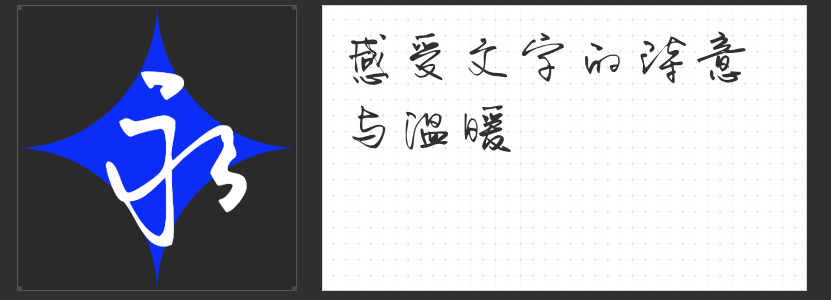
小豆岛手写字体推荐:四款风格迥异的设计利器
在商业设计中,手写字体的独特性和人文温度能瞬间提升作品的艺术质感。小豆岛系列字体以“传统笔意与现代设计融合”为核心理念,推出多款风格鲜明的手写字体,尤其适合海报、包装、品牌标识等场景。以下四款字体各具特色,可满足不同设计需求。
一、小豆岛默陌枝桠简
这款字体以“疏密有致”为设计核心,通过运笔节奏塑造线条粗细与节点,呈现出枯枝藤蔓般的自然形态。其水墨书写风格既有传统书法的写意感,又融入现代设计的留白美学,适合茶饮、文创、禅意主题的设计。例如,在茶包装中,小豆岛默陌枝桠简的飞白效果能传递“古朴自然”的品牌调性;在短视频字幕中,其灵动的笔触可增强画面叙事感。
二、小豆岛默陌乐童简
小豆岛默陌乐童简采用“上松下紧”的儿童字结构,笔画简单稚拙且宽细一致,完美复刻孩童书写时的天真感。这款字体尤其适合母婴产品、儿童绘本、教育机构等场景。例如,某早教品牌LOGO使用小豆岛默陌乐童简后,圆润的笔画与倾斜的字体结构传递出“活泼探索”的品牌理念;在电商促销海报中,其稚拙感能拉近与年轻家长的距离。
三、小豆岛默陌纸鸢草书简
小豆岛默陌纸鸢草书简以“连笔流畅”为特色,笔画恣意舒展如风筝线般飘逸,中宫放大与笔画加粗的设计则提升了辨识度。这款字体兼具艺术性与实用性,适合运动品牌、音乐节、快消品等动态场景。例如,某运动鞋广告使用小豆岛默陌纸鸢草书简后,飞白的笔触与倾斜的字体结构强化了“速度与力量”的视觉冲击;在社交媒体短视频中,其流畅的连笔可提升字幕的阅读流畅度。
四、小豆岛默陌肥圆手写简
小豆岛默陌肥圆手写简以“丰腴圆润”为造型基础,采用轻松自由的水墨笔触,笔画节点随性而不失平衡。这款字体尤其适合食品包装、萌系IP、生活美学类设计。例如,某零食品牌包装使用肥圆手写简后,圆润的笔画与饱满的字形传递出“温暖治愈”的品牌温度;在卡通形象设计中,其不拘小节的笔触可增强角色的亲和力。
小豆岛系列字体通过“传统笔意+现代设计”的双重基因,为设计师提供了丰富的表达工具。无论是追求禅意留白、孩童稚趣,还是动态流畅、治愈圆润,这四款字体均能以独特的视觉语言,让设计作品更具温度与辨识度。